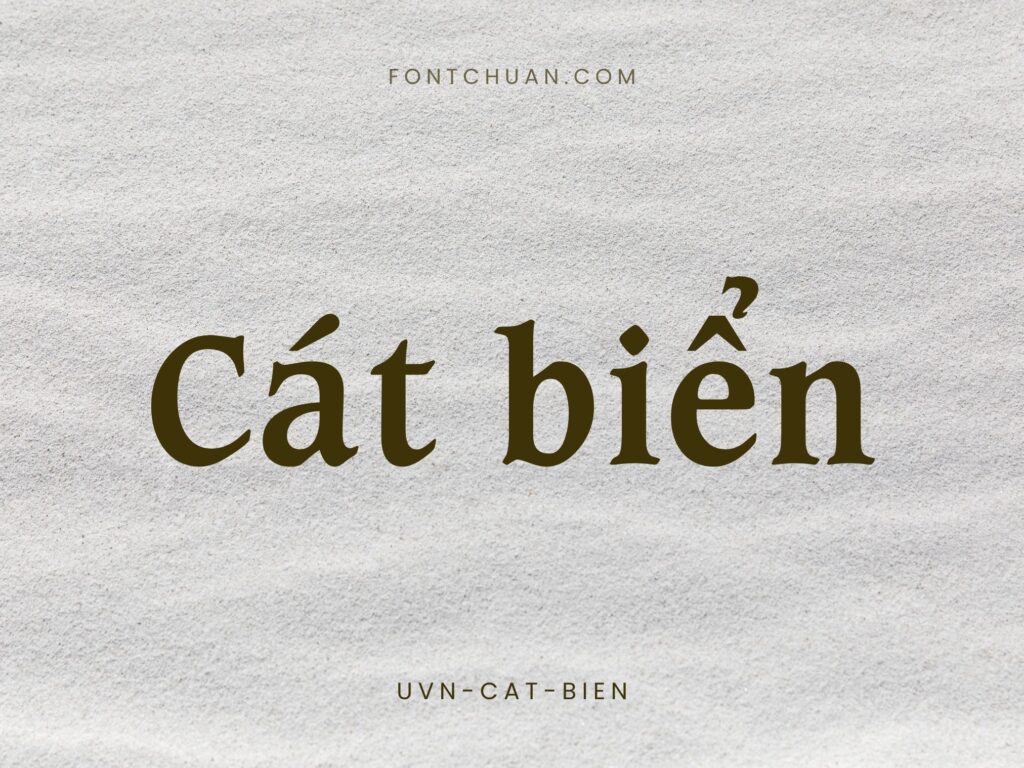
Font UVN Cat Bien Việt Hóa
UVN Cát Biển là một kiểu font mang hơi thở biển cả, thể hiện qua nét chữ mềm mại, uyển chuyển và có phần phóng khoáng. Phong cách thiết kế của font này vừa mang nét hiện đại, vừa gợi cảm giác gần gũi với thiên nhiên, rất phù hợp với các chủ đề du lịch, văn hóa hoặc các thiết kế gắn liền với khung cảnh biển. Font này đã được thành viên Font Chuẩn chọn lọc và sưu tầm để phục vụ nhu cầu thiết kế sáng tạo, ứng dụng thực tế vào nhiều dự án truyền thông, in ấn, hoặc nhận diện thương hiệu mang màu sắc địa phương.
Các chữ cái trong UVN Cát Biển có độ cong nhẹ, cách điệu ở các nét nối và độ dày vừa phải, giúp font dễ đọc nhưng vẫn giữ được cá tính riêng biệt. Phù hợp để sử dụng trong các ấn phẩm quảng bá du lịch, biển đảo, banner mùa hè hoặc poster lễ hội. Font này đặc biệt lý tưởng cho các ngành nghề như quảng cáo, ẩm thực, bất động sản, công nghệ và giáo dục. Các sự kiện như lễ hội, Tết, Trung thu, Valentine hay sinh nhật đều có thể ứng dụng hiệu quả với font này.